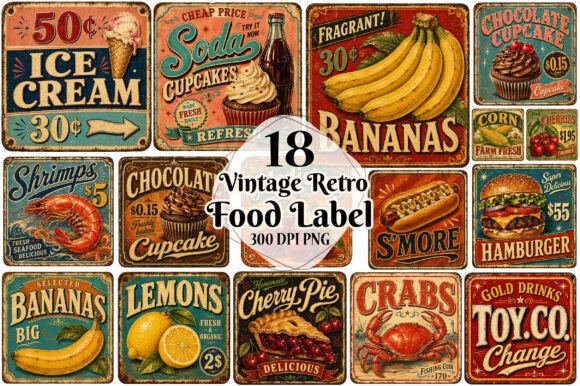
Vintage Retro Food Label & Signage
Doğru tasarım öğelerini bulmak zor olabilir, ancak Vintage Retro Food Label & Signage, çalışmanızı anında bir üst seviyeye taşıyan olağanüstü bir koleksiyon sunar.
İster İsteğe Bağlı Baskı (POD) ürünleri, ister düğün davetiyeleri veya sosyal medya grafikleri oluşturuyor olun, Vintage Retro Food Label & Signage ideal bir uyumdur.